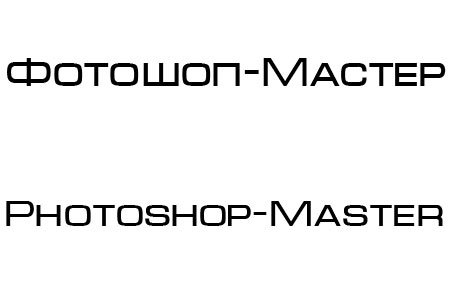
поддержу, шрифт прияяятный)
спасибо за шрифт но отсутствует символ + , погоду выбивает вместо +18 , -18 , ни есть гуд , можно как то поправить ?
очень приятный шрифт, спасибо